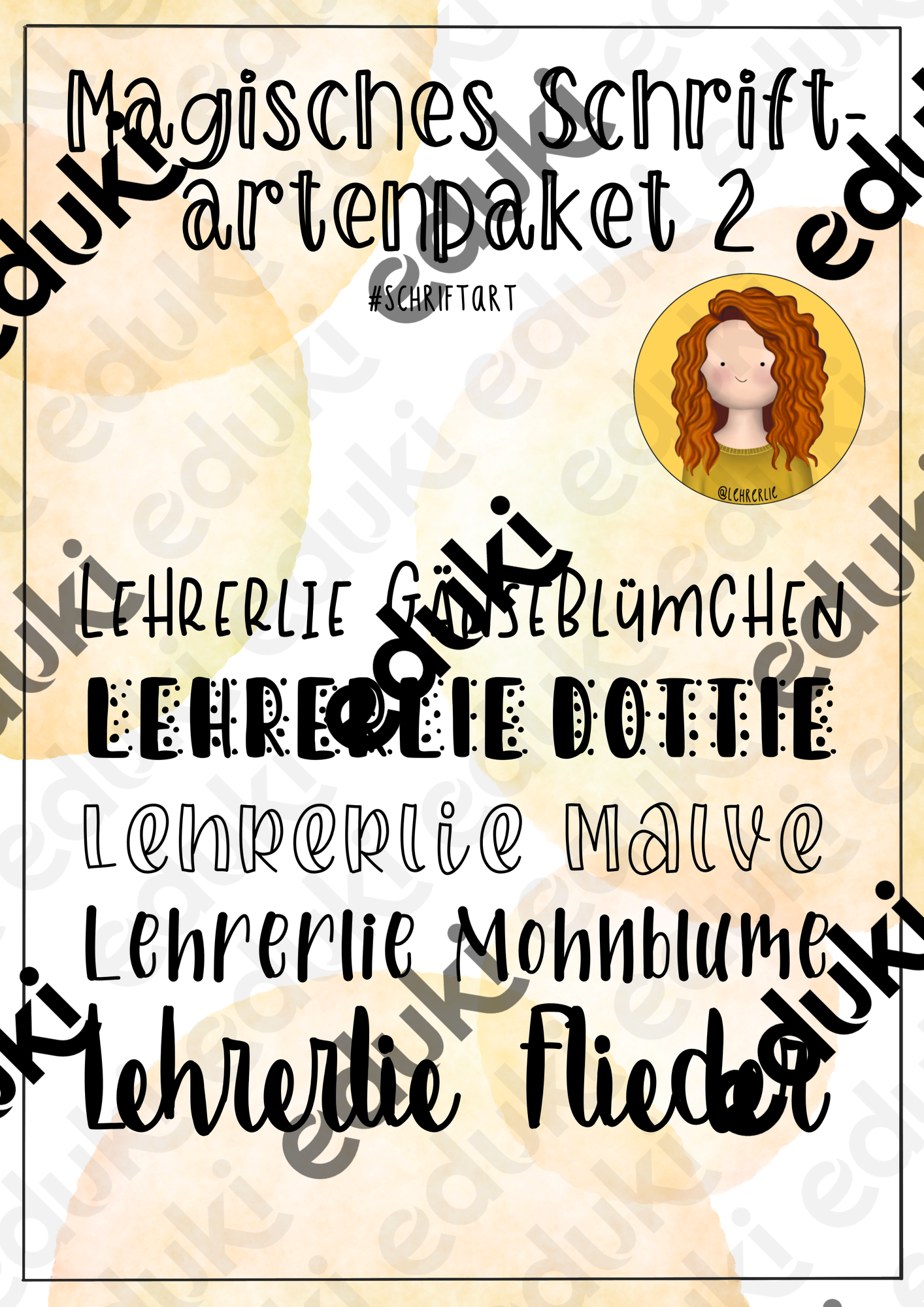
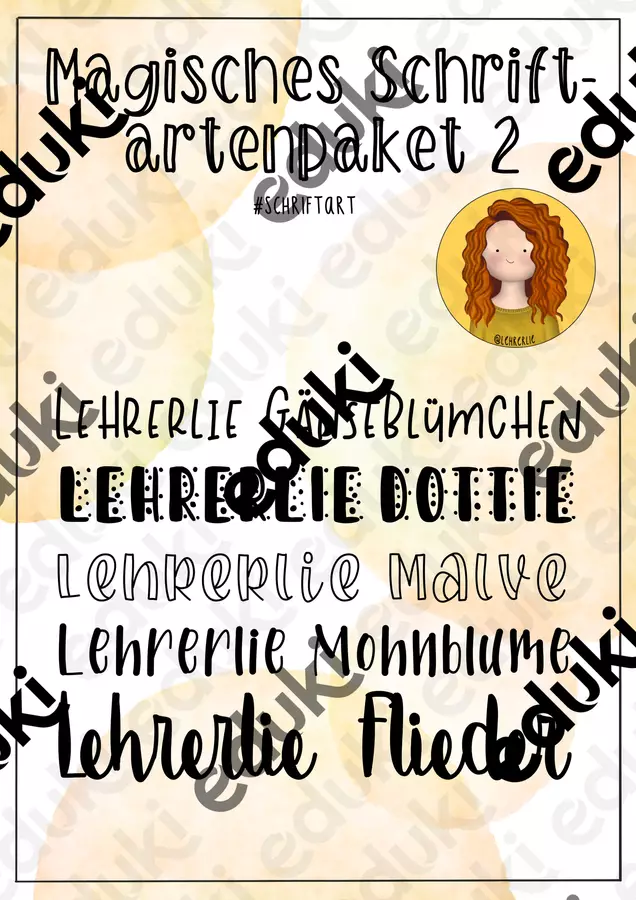
selbst erstellte Schriftarten - Magisches Schriftartenpaket II - 5 Schriftarten - Pinselkomponistin - Deckblatt
Uuuuuund hier bekommt ihr das zweite magische und gigantische Schriftartenpaket von mir. Wie das erste stehen auch hier die kreativen Gestaltungen von Überschriften im Vordergrund - Umlaute, Zahlen und die wichtigsten Satzzeichen sind aber jeweils dabei.
Magisches Schriftartenpaket II - 5 Schriftarten